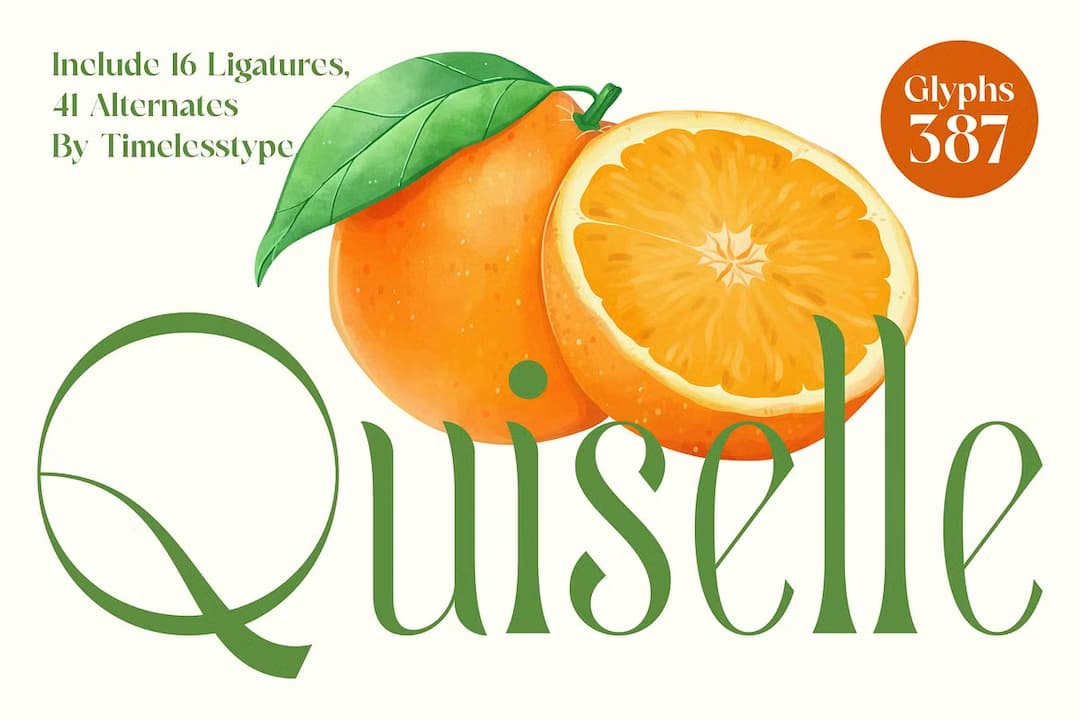
クラッシーなフレアセリフ?ディスプレイ。コントラストの強いストロークに大きなフレアが付いた優雅な雰囲気の書体で、全体的にコンデンスなグリフながら、O などの円を基本にした字はそのまま真円に近いプロポーションで、他の字との差がおもしろいアクセントになっている。各字には小さなスワッシュの付いたオルタネートがあり、小文字にはリガチャーが若干あり。イタリックと2スタイル。